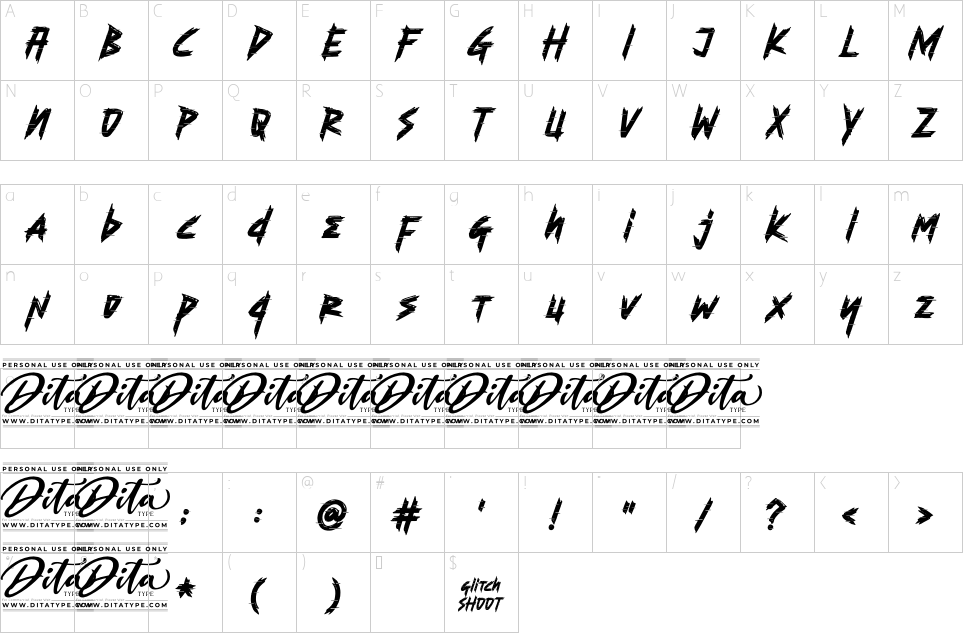
Glitch Shoot Font – Download Grátis
A Glitch Shoot é uma fonte criada por Dita Type que traz um toque único de glitch nos seus traços levemente irregulares e vibrantes. Esta fonte, disponível tanto para sistemas Windows quanto Mac, adiciona um toque moderno e inovador a qualquer projeto gráfico ou design digital. Suas linhas desenformadas e seu estilo disruptivo permitem uma aplicação versátil que pode ser utilizada em logotipos, publicações digitais e até mesmo no design de ícones. Com um design minimalista e vibrante, a Glitch Shoot é uma opção perfeita para quem deseja dar um toque único ao seu trabalho. Descarregada mais de 1280 vezes, você pode garantir que estejam disponíveis quantidades suficientes para o uso pessoal sem preocupações legais. Não perca tempo e descubra por si mesmo a essência da Glitch Shoot!